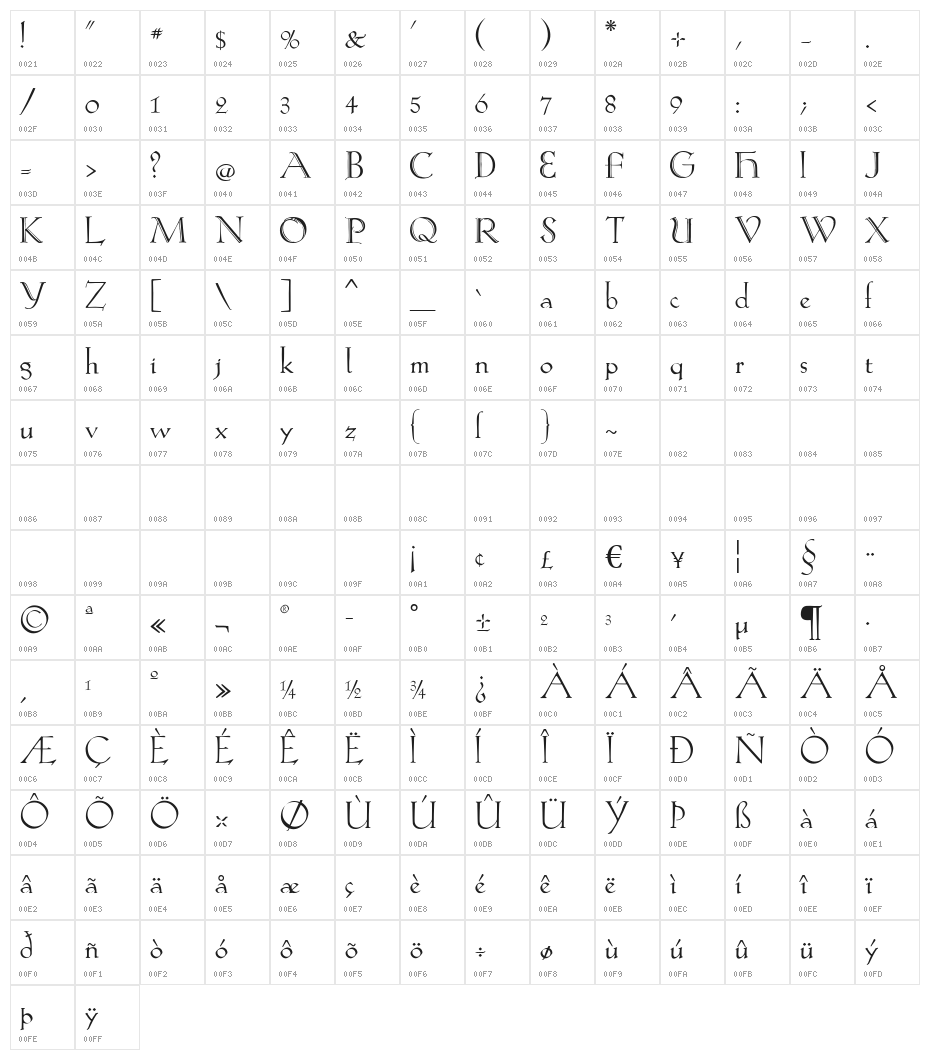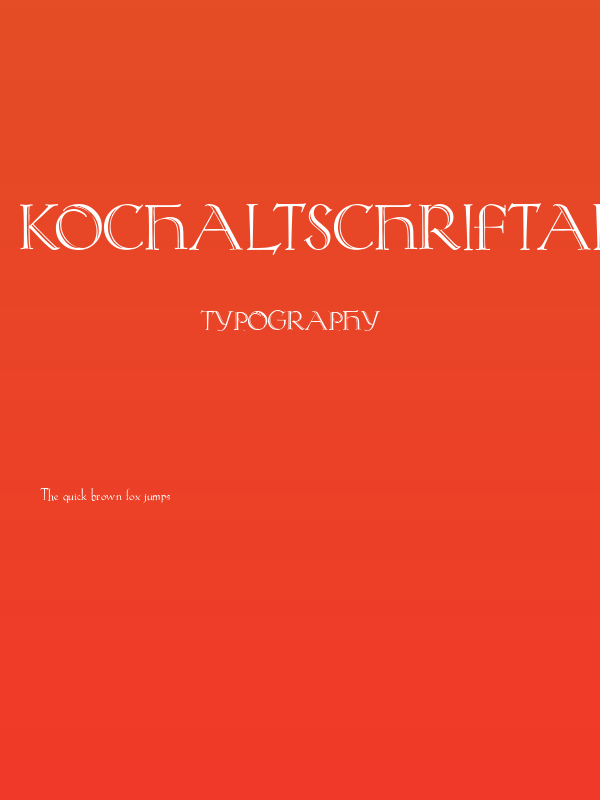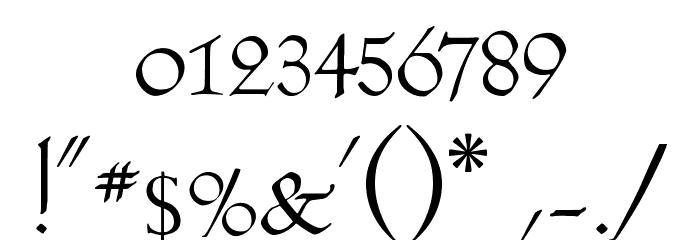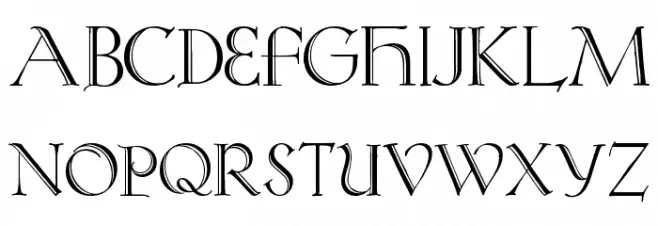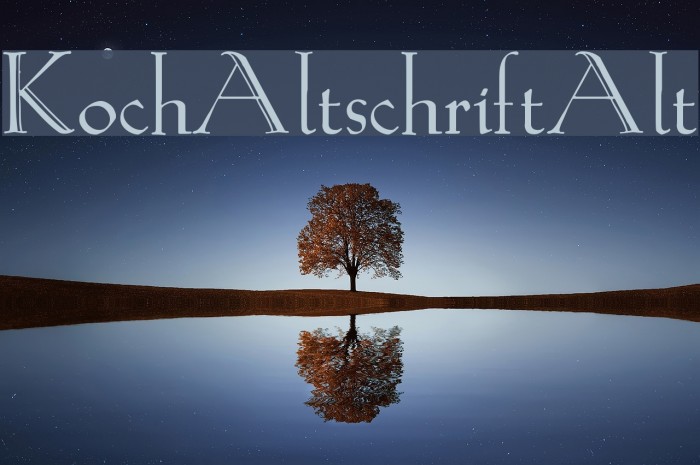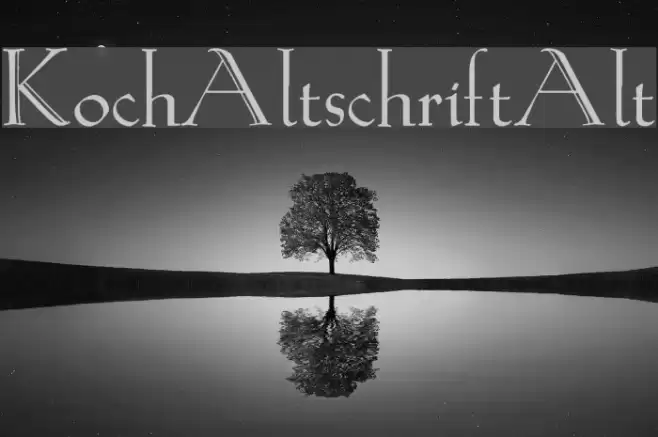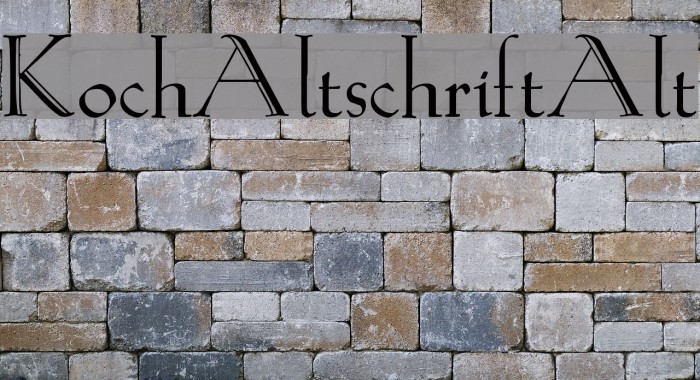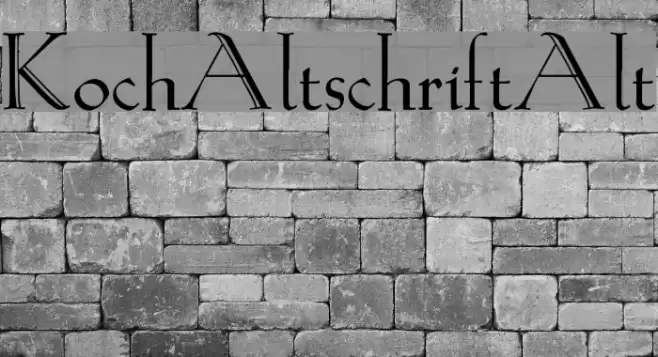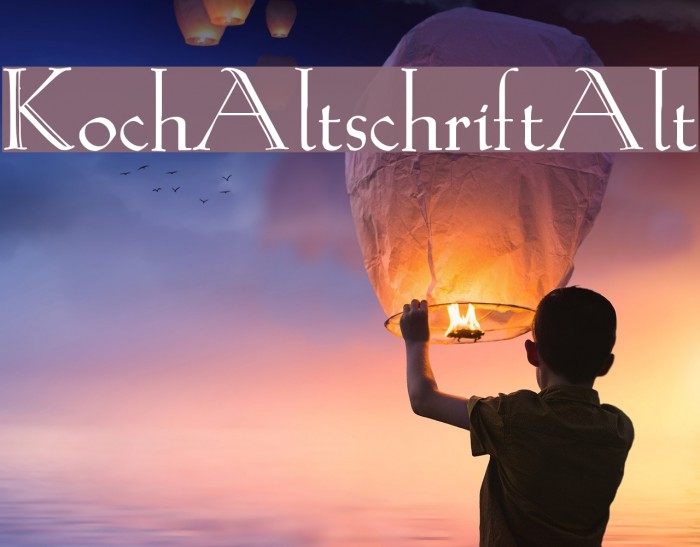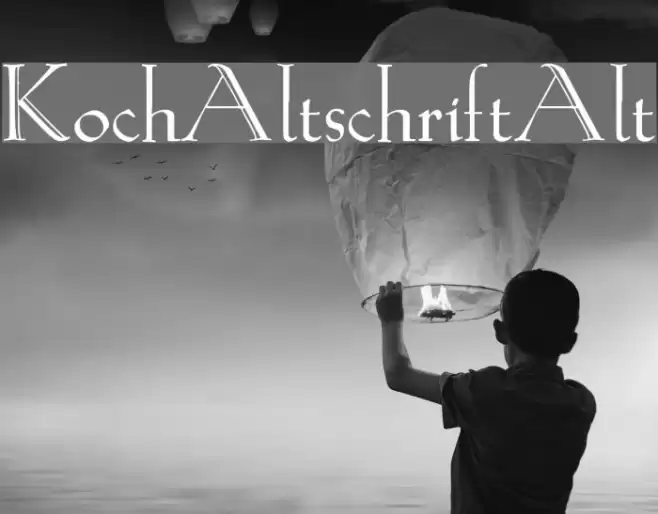
KochAltschriftAlt Font
| Gesamtstil | Vintage |
| Vorgeschlagene Projekte | Ideal for wedding invitations, historical publications, or branding that requires a touch of elegance and tradition. |